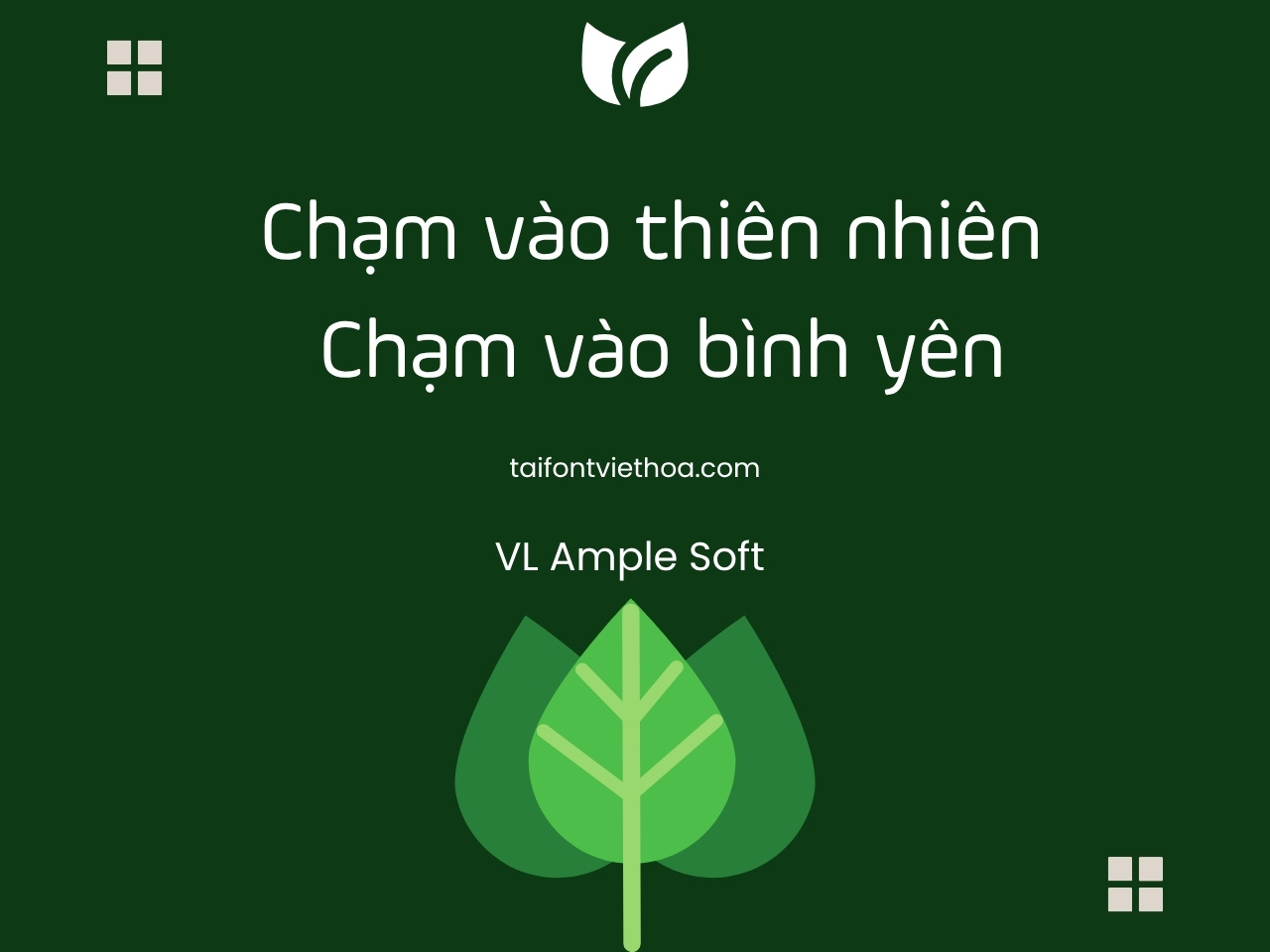
Font việt hóa VL Ample Soft đầy đủ
Tác giả Font: Aakash Soneri
Giới thiệu về font VL Ample Soft
VL Ample Soft là một kiểu chữ sans-serif mang phong cách hiện đại, mềm mại và thân thiện. Font thuộc bộ Ample gốc do ITF (Indian Type Foundry) thiết kế, nổi bật với các đường nét bo tròn và tỷ lệ chữ hài hòa, giúp tăng khả năng đọc và tạo cảm giác dễ chịu. Phiên bản Việt hóa trọn bộ do Font Việt Linh thực hiện, hỗ trợ đầy đủ tiếng Việt với hệ dấu rõ ràng, thẩm mỹ. Font còn tương thích với hơn 60 ngôn ngữ khác nhờ tích hợp bảng mã Latin Extended. VL Ample Soft đã được taifontviethoa.com chọn lọc và ứng dụng thực tế trong nhiều dự án UX/UI, nhận diện thương hiệu và thiết kế số tại Việt Nam.
Đặc điểm thiết kế và ứng dụng của VL Ample Soft
VL Ample Soft nổi bật với cấu trúc không chân (sans-serif), bo góc nhẹ nhàng, tạo cảm giác mềm mại nhưng vẫn chuyên nghiệp. Font có nhiều trọng lượng từ Light đến Bold, phù hợp cả tiêu đề và văn bản nội dung. Khoảng cách chữ thoáng, thân thiện với giao diện người dùng và các ứng dụng hiển thị số.
Font đặc biệt phù hợp cho các dự án thiết kế website, app mobile, hồ sơ công ty, tài liệu doanh nghiệp, ấn phẩm marketing hoặc bao bì sản phẩm công nghệ. Ngành nghề lý tưởng bao gồm: công nghệ, giáo dục, y tế, truyền thông số, bất động sản và startup sáng tạo.